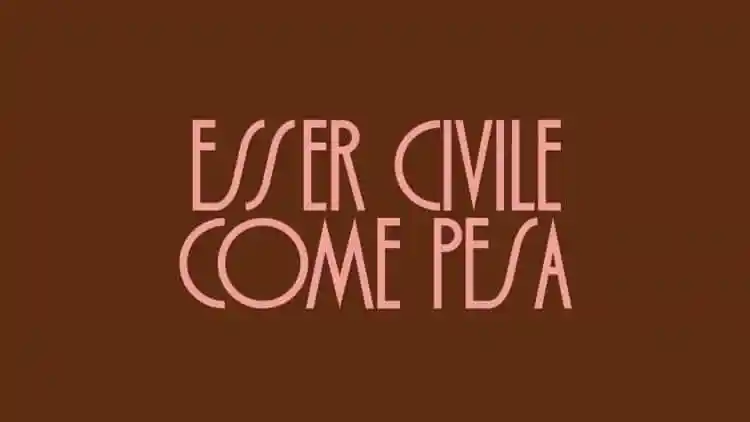
Gelosa Cara Display Font
A Gelosa Cara Display Font é uma escolha perfeita para quem busca uma fonte que transmite modernidade com um toque nostálgico, inspirada nos tipos de caracteres do início dos anos 80. Suas linhas limpas e seu design autêntico a fazem se destacar em várias aplicações gráficas, como as legendas de vídeos no vlog, criação de logotipos, banners para web na área da moda, promocionando músicos ou cantores e até mesmo publicidade de restaurantes e cafés. Esta fonte é uma ótima opção para quem busca um toque especial que traga um ar retrô ao seu design sem se perder em modernidade. A sua natureza limpa e autêntica faz dela uma escolha versátil, garantindo que a mensagem esteja sempre presente e claramente visível, seja ela o nome de um restaurante sofisticado ou apenas uma frase única para um post de Instagram.